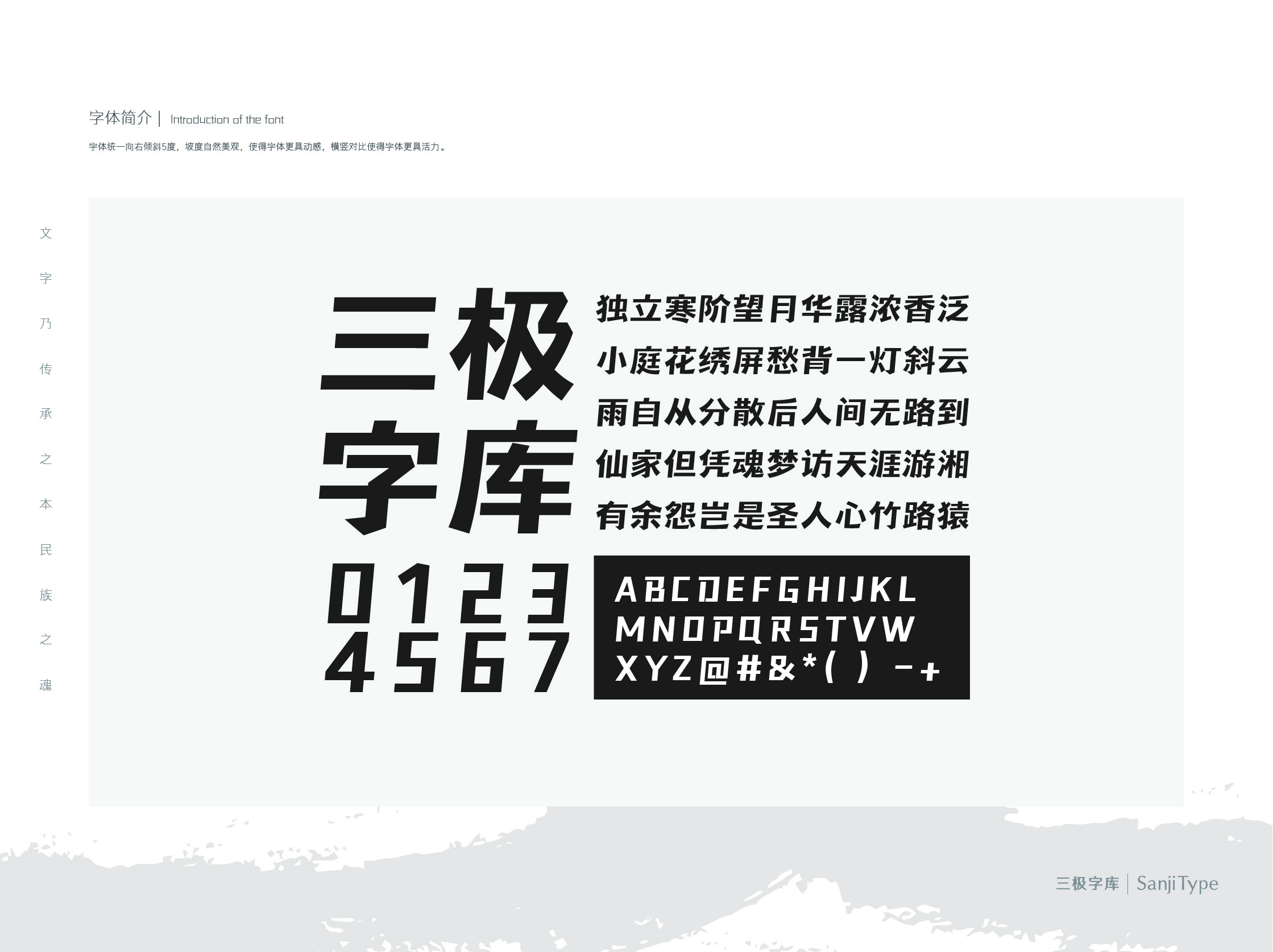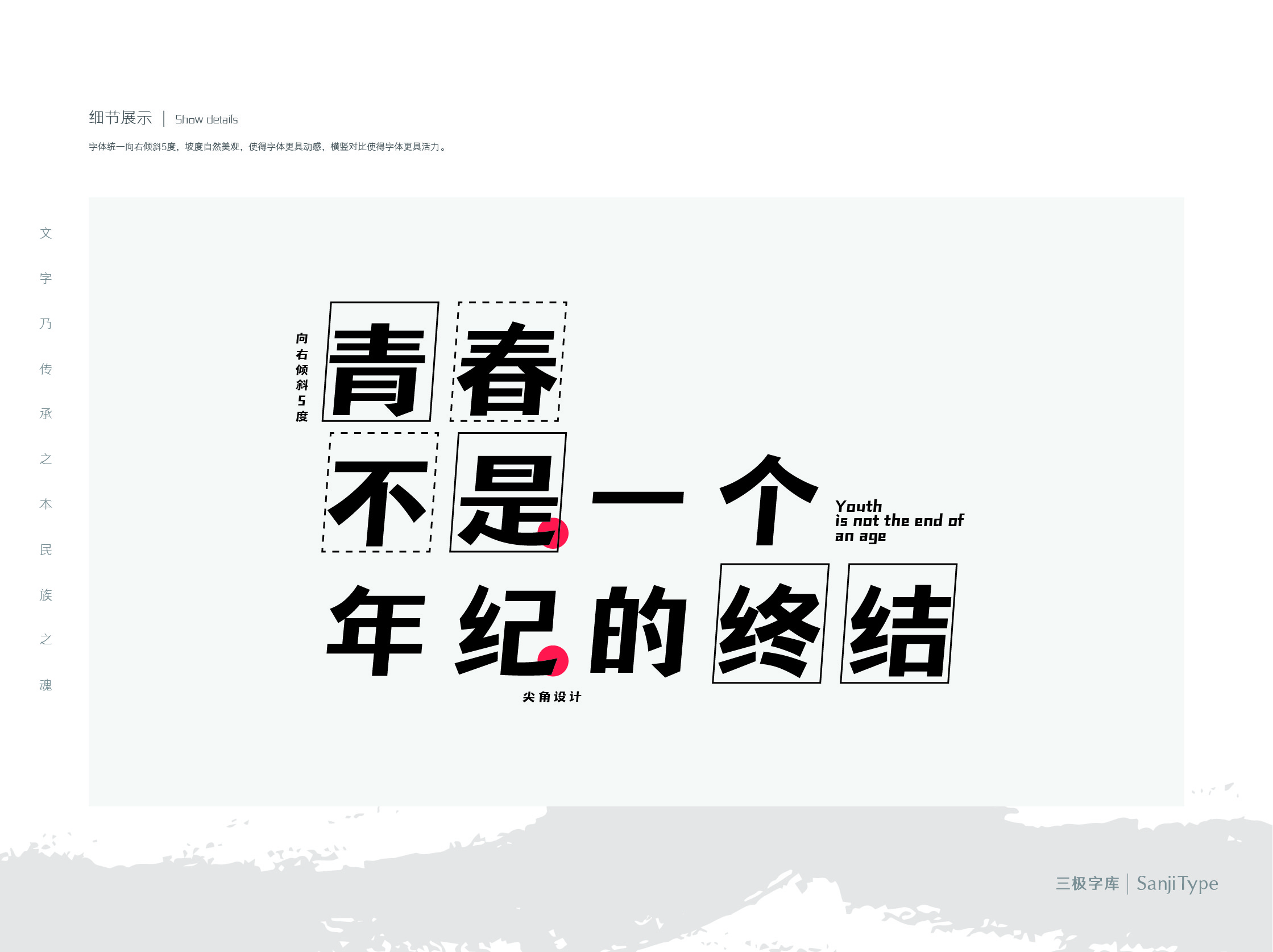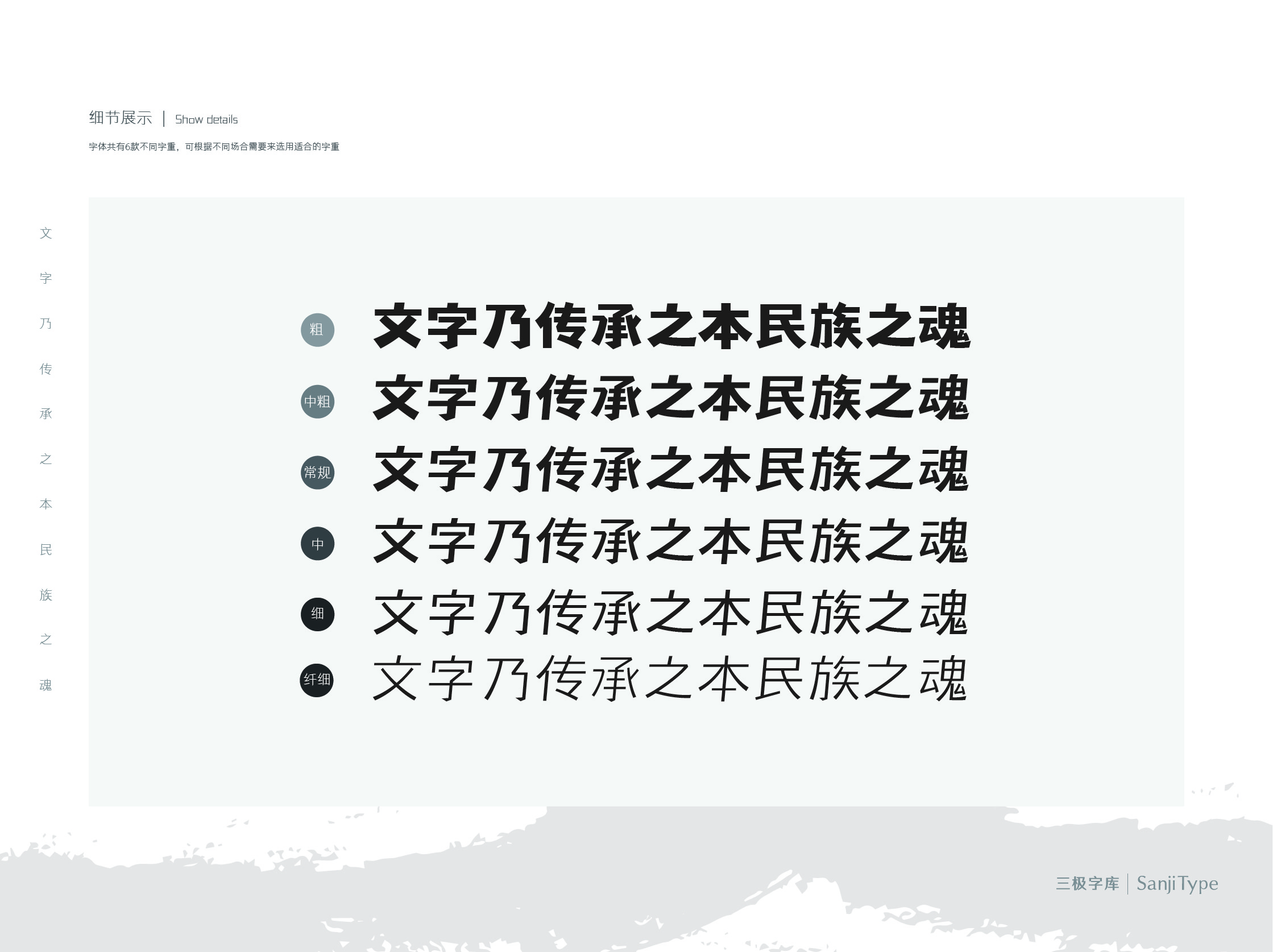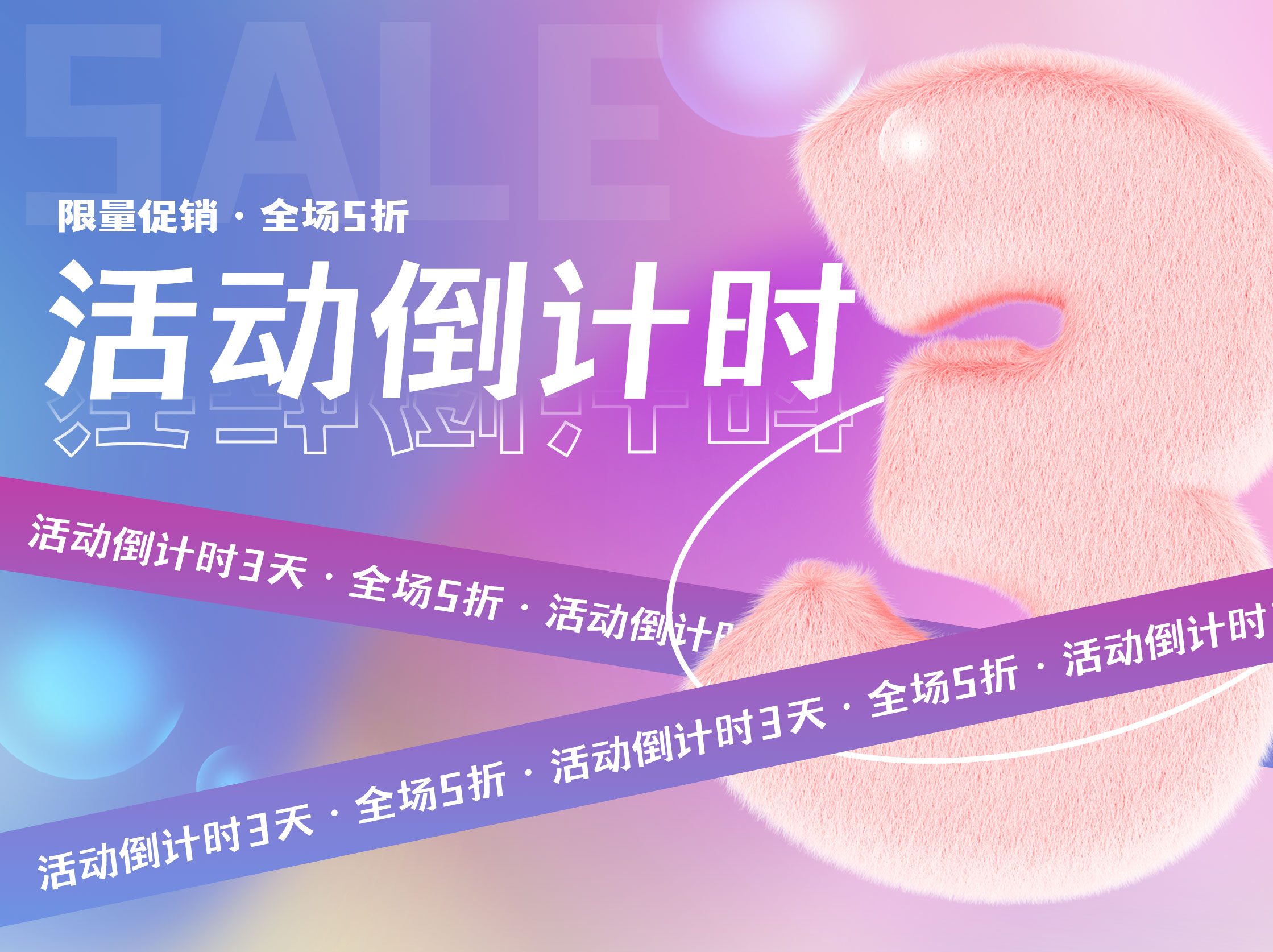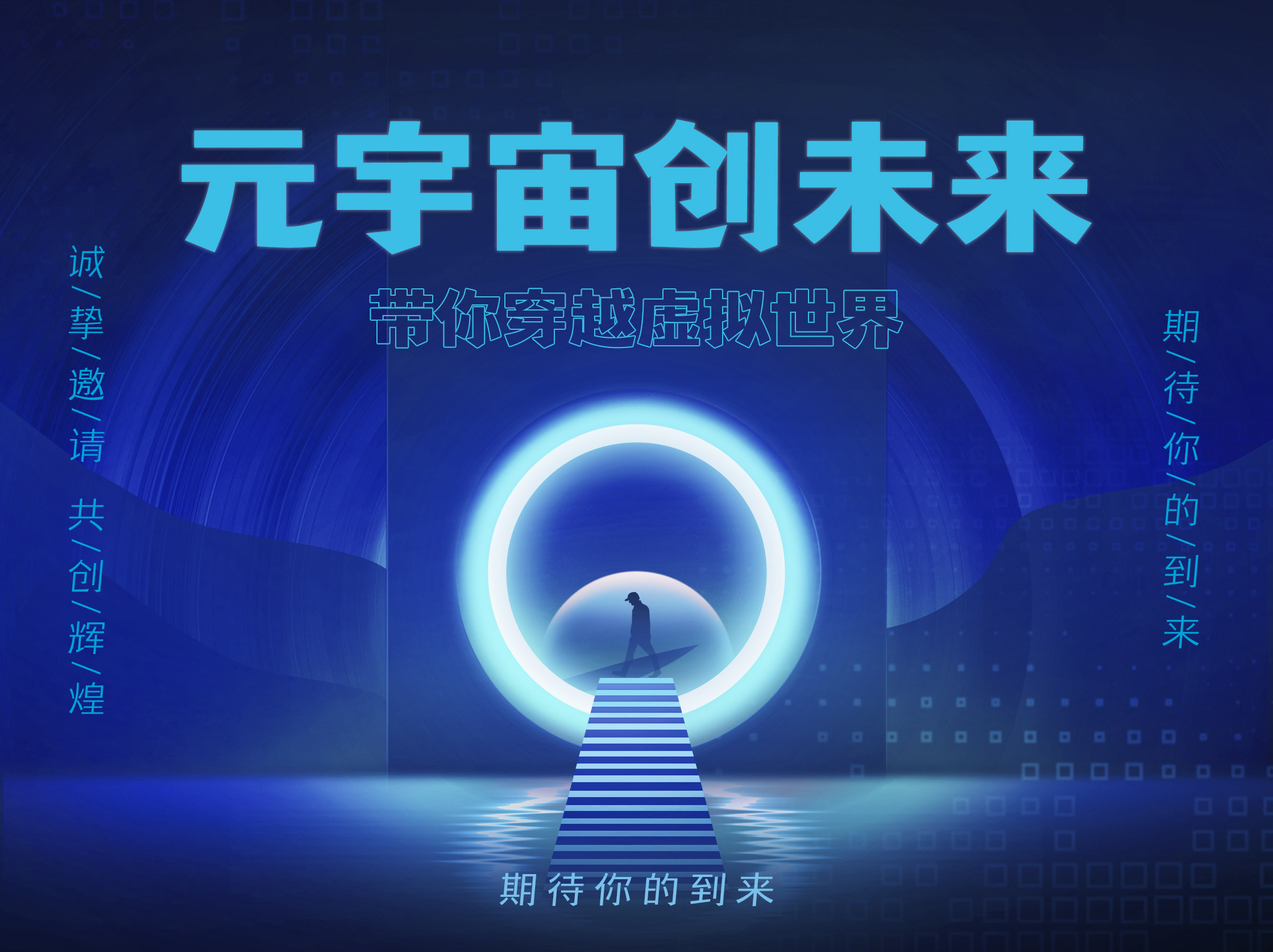
三极铿锵体家族
将字体统一向右倾斜5度,坡度自然美观,使得字体更具动感,横竖对比使得字体更具活力。含有六个字重,随着字重的减小,字体的横竖对比更加鲜明。在细节处,字体笔画始末两端有尖角,使得字体更加整洁。字体的字型倾斜浑厚,因此非常适合用作中文LOGO设计,也可以应用在banner设计、海报设计和 PPT 标题上。